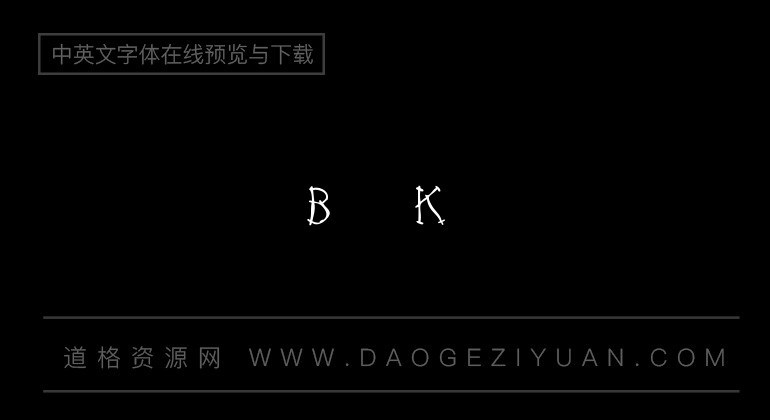
Billie Kid
Billie Kid 是一款时髦的手写字体,由独立设计师Joanne Marie设计。它的特点是流畅的笔画和漂亮的连接点,使其看起来非常自然和人性化。这个字体的灵感来自于美国西部的文化和历史,因此它不仅适用于时尚和现代的设计项目,还可以用于表现出乡村或西部主题的设计。Billie Kid 字体包含大小写字母、数字和标点符号,支持多种语言,可以用于海报、标志、包装、品牌、广告等多种设计项目。
Billie Kid是一款非常不错的手写艺术字体,具有很好的视觉感,适合于文化类的宣传设计、商业类品牌的广告和产品包装设计以及个性化文字排版等较多场景。
Billie Kid字符映射图